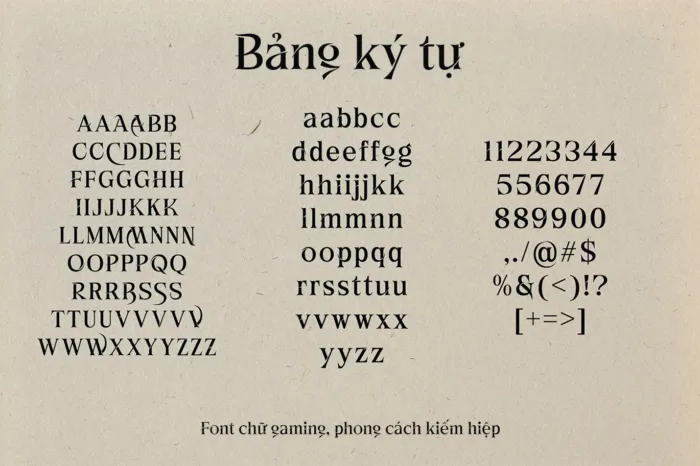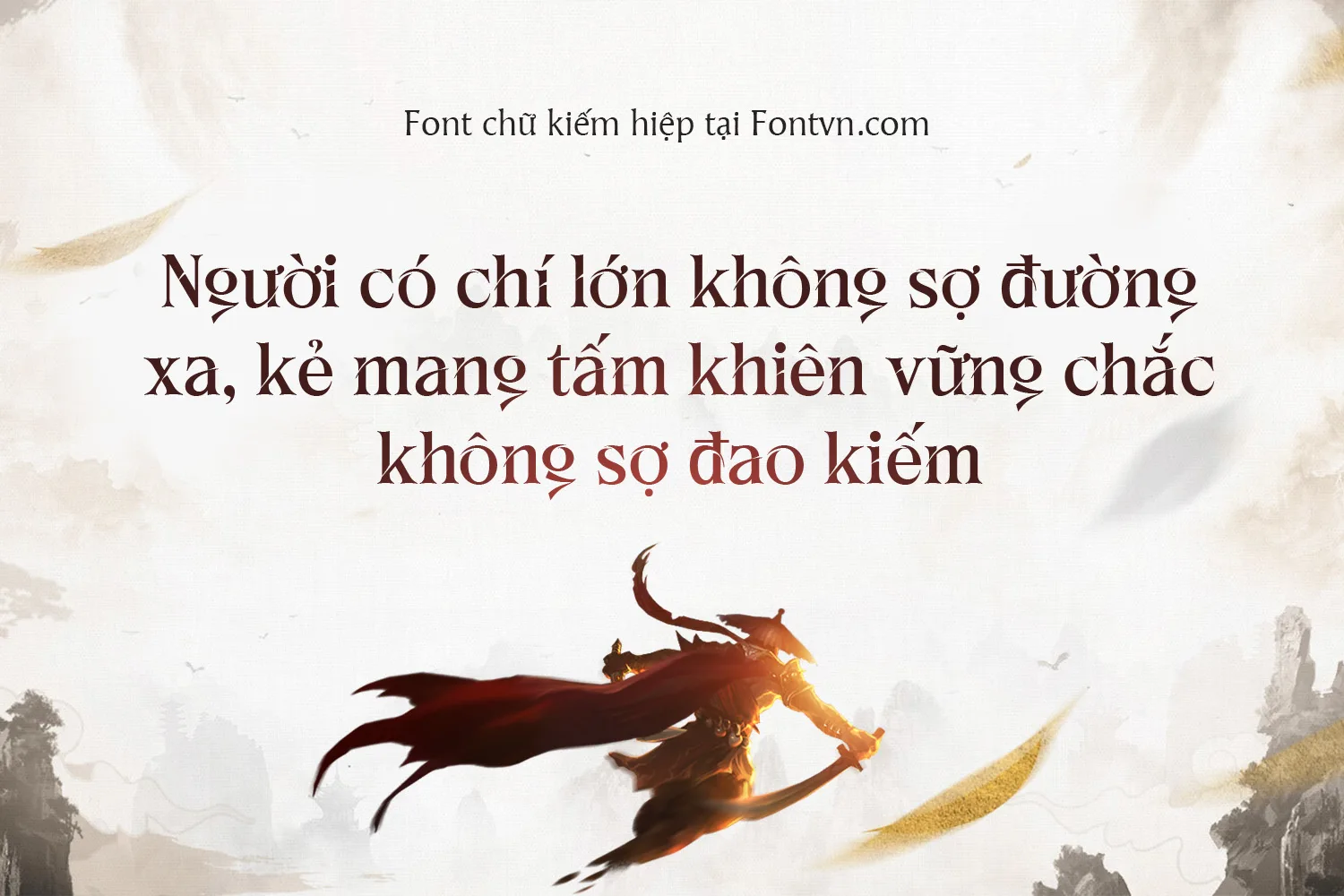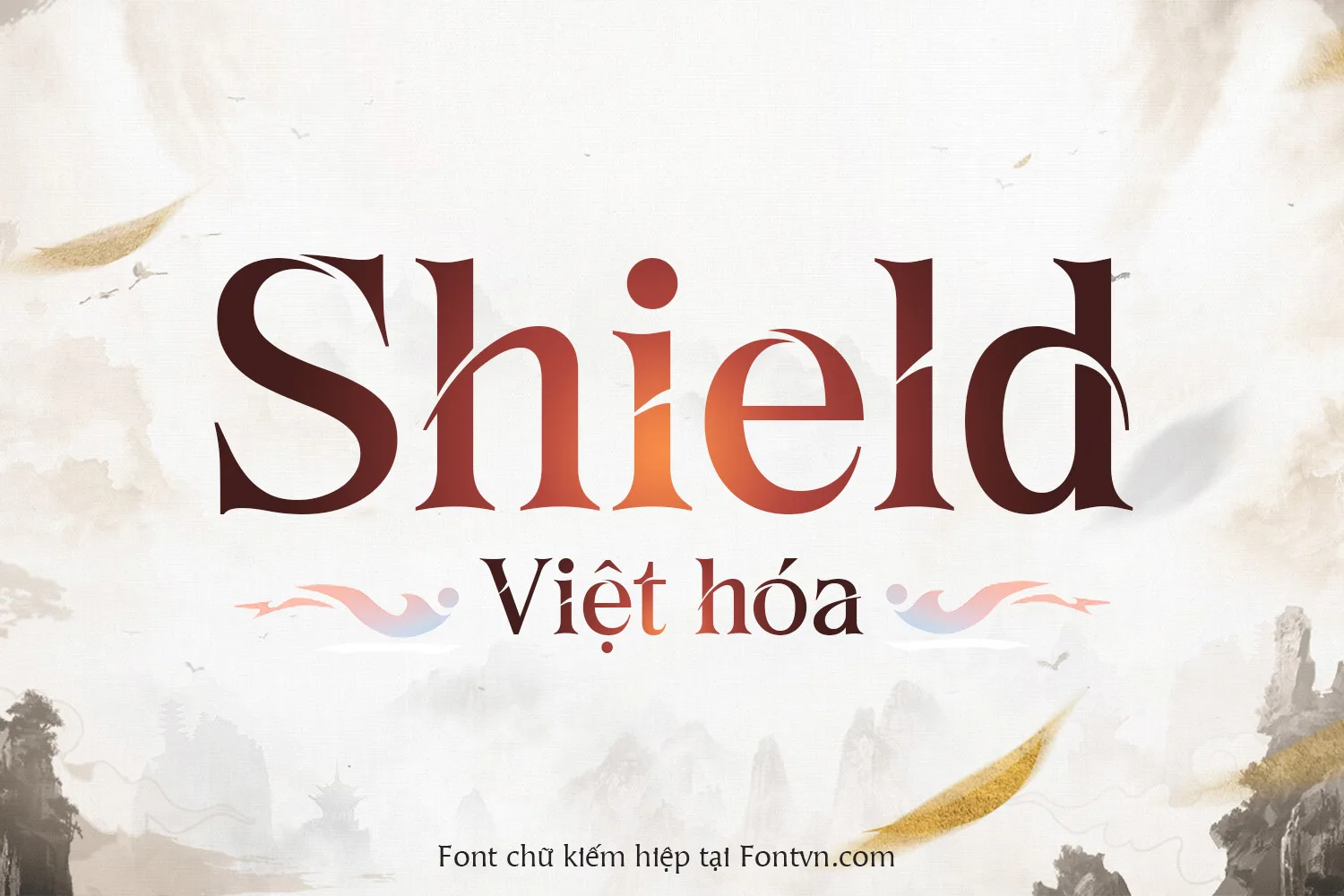
DVN Shield – Font chữ tiếng Việt phù hợp cho Logo, Game kiếm hiệp
DVN Shield là font chữ tiếng Việt do tôi thiết kế, mang phong cách mạnh mẽ và uy nghi, lấy cảm hứng từ kiến trúc Gothic cổ điển kết hợp tinh thần chiến binh. Các đường nét sắc sảo, chân chữ nhọn và cấu trúc vững chắc giúp font thể hiện rõ khí chất quyền lực, dứt khoát nhưng vẫn tinh tế trong từng chi tiết.
Với bộ ký tự tiếng Việt đầy đủ, DVN Shield đáp ứng hoàn hảo nhu cầu thiết kế cho thị trường Việt Nam, từ logo thương hiệu, tiêu đề game kiếm hiệp, poster sự kiện cho đến các dự án fantasy, RPG. Khi xuất hiện trên ấn phẩm, font mang lại cảm giác cổ điển xen lẫn hiện đại, giúp nội dung trở nên nổi bật và ghi dấu ấn mạnh mẽ trong mắt người xem.